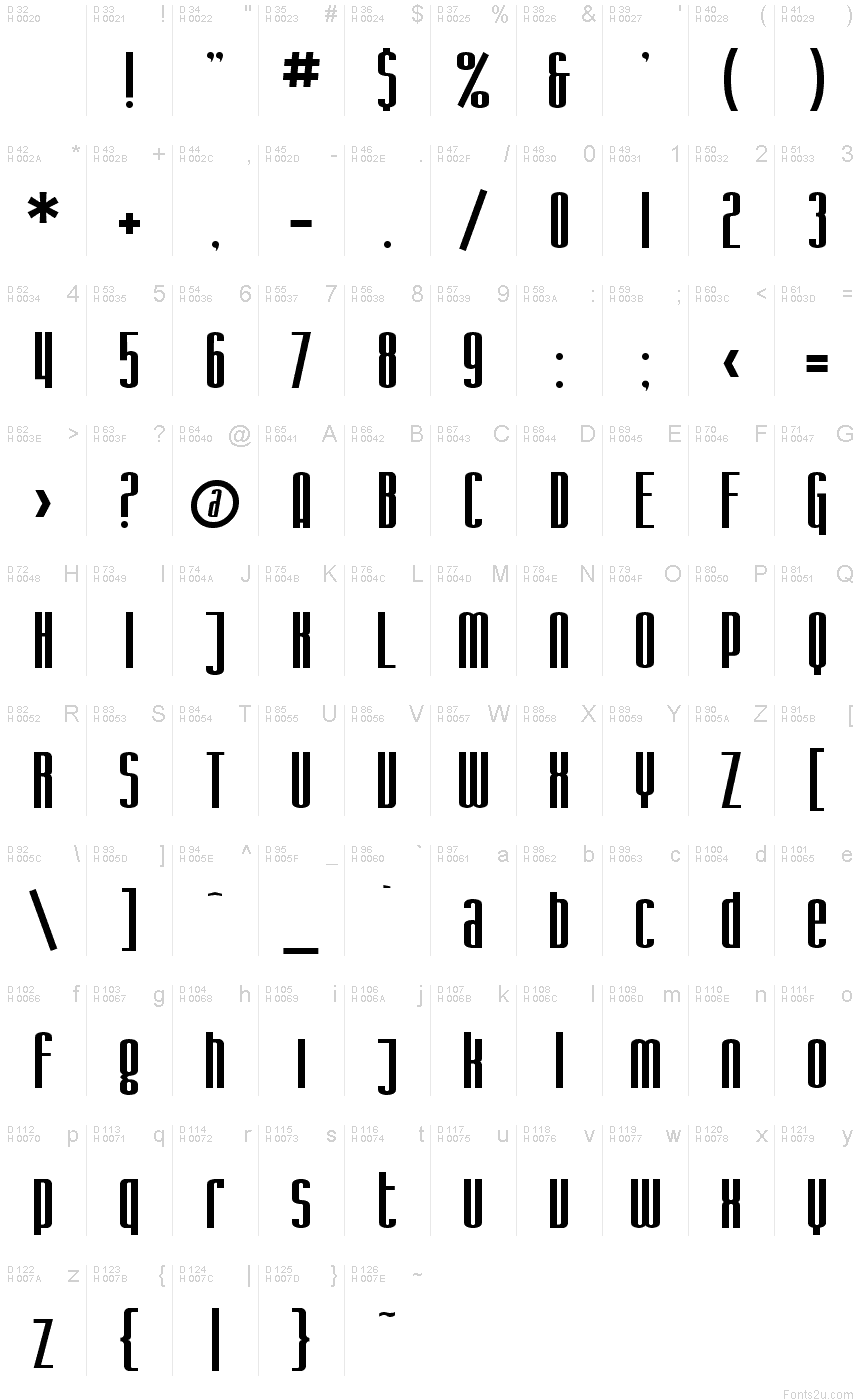
SF Iron Gothic od ShyFoundry to darmowy, industrialny krój displayowy w stylu Art Déco o wyrazistym, surowym rytmie. Wysokie, wąskie litery łączą ostre kąty proste z szerokimi łukami, dzięki czemu projekt przywodzi na myśl mechaniczną typografię miejskich szyldów.
Świetnie sprawdza się na plakatach, okładkach albumów, w tytułach i na opakowaniach, gdzie potrzebny jest wąski, architektoniczny charakter. Jako darmowy font, sprawdzi się również w projektach brandingowych, grafikach eventowych i krótkich nagłówkach, zwłaszcza gdy chcesz, aby pionowa dynamika liter grała główną rolę wizualną.
SF Iron Gothic
ShyFoundry
Derek Vogelpohl